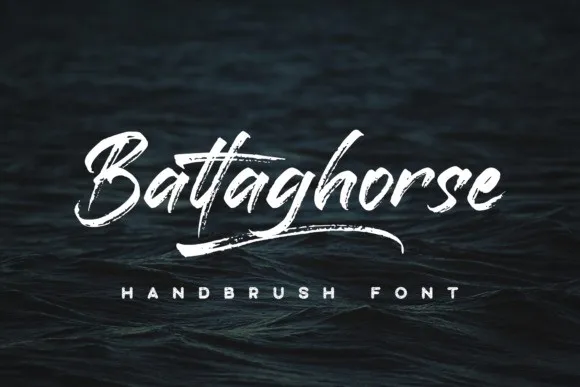
Battaghorse Brush Font Demo – Download Grátis
Olá, amigos. Estamos encantados de apresentar a vocês Battaghorse Font, uma nova opção na categoria de fontes Script para projetos de design que exigem um toque personalizado. Esta fonte é uma criação criativa e contemporânea feita à mão por 24Design, e contém detalhes interessantes como underscores, alternativas e ligaturas. A Battaghorse Font tem uma escrita rápida com texturas e swashes, tornando-a perfeita para qualquer projeto de design que exija uma aparência única e personalizada. Através da sua fluida e versátil escrita, a Battaghorse Font se destaca como uma opção versátil. Seja para logotipos, roupas ou mesmo embalagens de produtos, esta fonte traz um toque único à qualquer projeto, tornando-o mais intrigante e diferenciado. A sua textura e swashes garantem que a Battaghorse Font se destaque, especialmente em aplicações como t-shirts, capas de mochila e até mesmo nas etiquetas de produtos. Para os desafios e trabalhos exigentes, a Battaghorse Font é uma escolha inteligente. Com seu estilo único, ela certamente tornará seus projetos mais inovadores e interessantes. Seja qual for o seu projeto, esta fonte vem para fornecer um acelerador de tipos que irá transformar qualquer texto em algo realmente especial. Adquira a Battaghorse Font hoje mesmo!